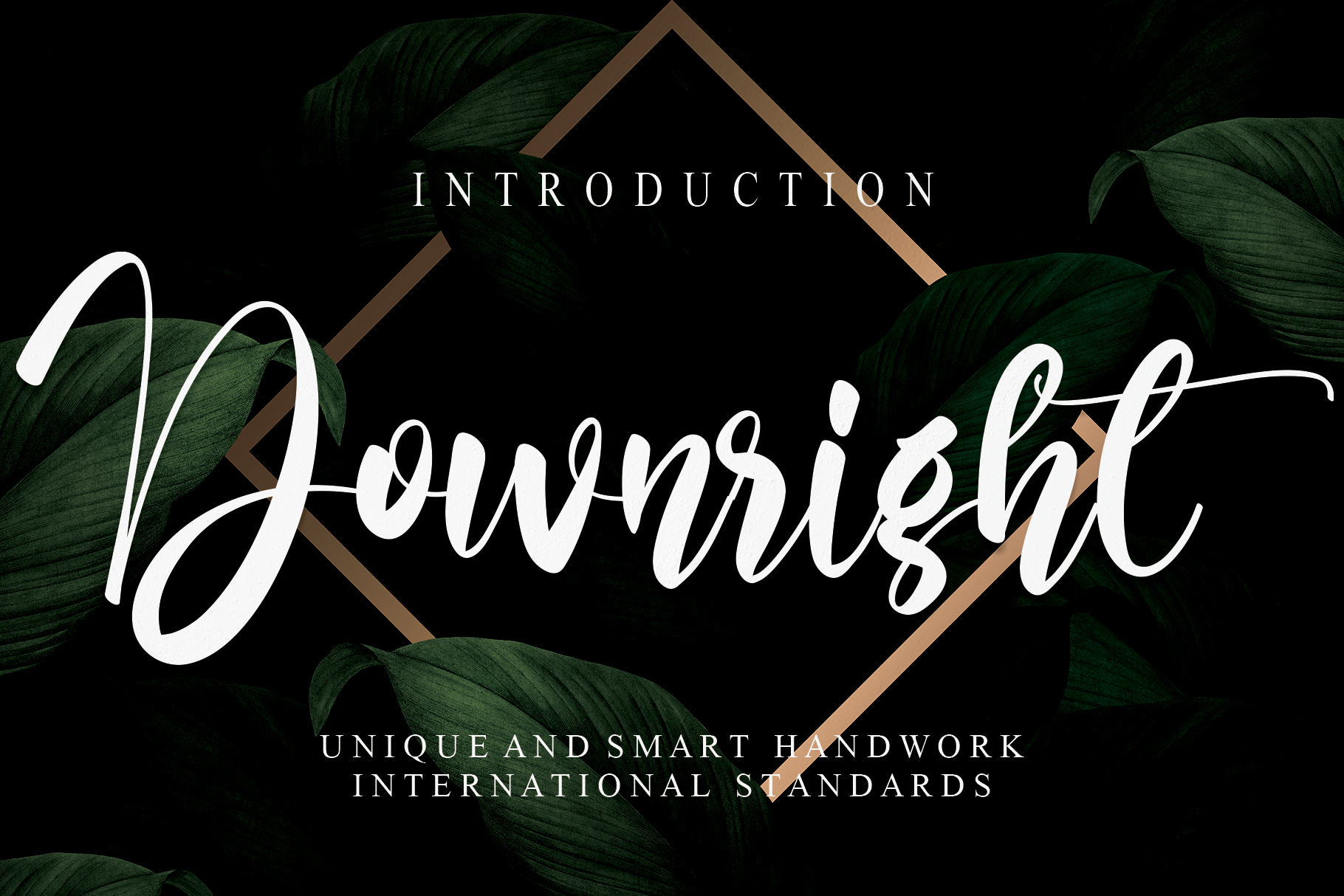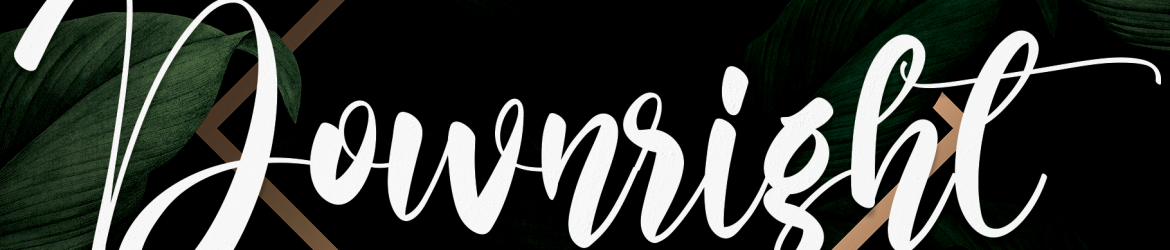
Descubra Downright Script Font, uma elegante tipografia script que vai transformar seu próximo design no brilho especial que ele merece. Inspirada nos traços delicados e românticos das escritas manuscritas, esta fonte é versátil o bastante para atender a um vasto leque de aplicações, desde cartões de cumprimentos até atividades criativas criadas por crianças. É uma escolha perfeita para adicionar um toque de simplicidade e charme ao seu projeto. A Downright Script é perfeitamente equipada para tornar sua próxima criação em algo realmente especial, garantindo que ela seja lembrada com uma pitada de suavidade e sofisticação. Não importa qual design você está criando, esta fonte manuscrita certamente vai deixá-lo admirado por sua habilidade de transformar qualquer trabalho num verdadeiro truque de mágica.